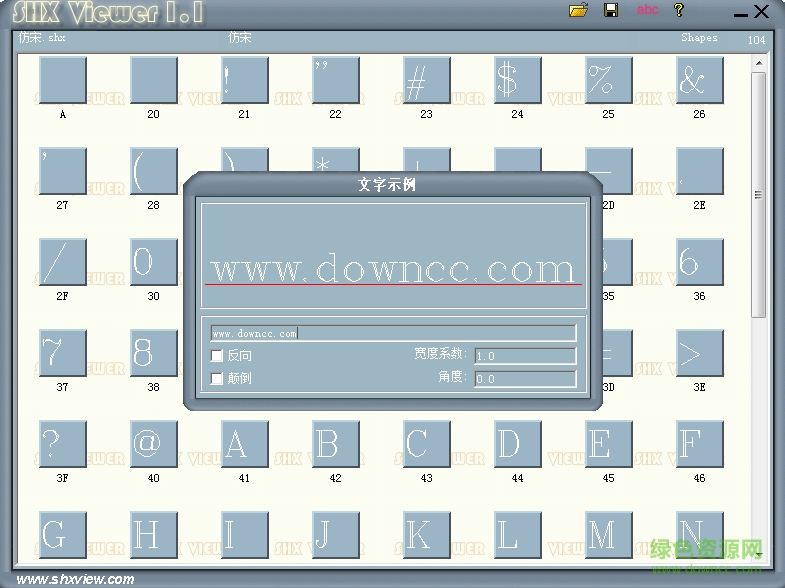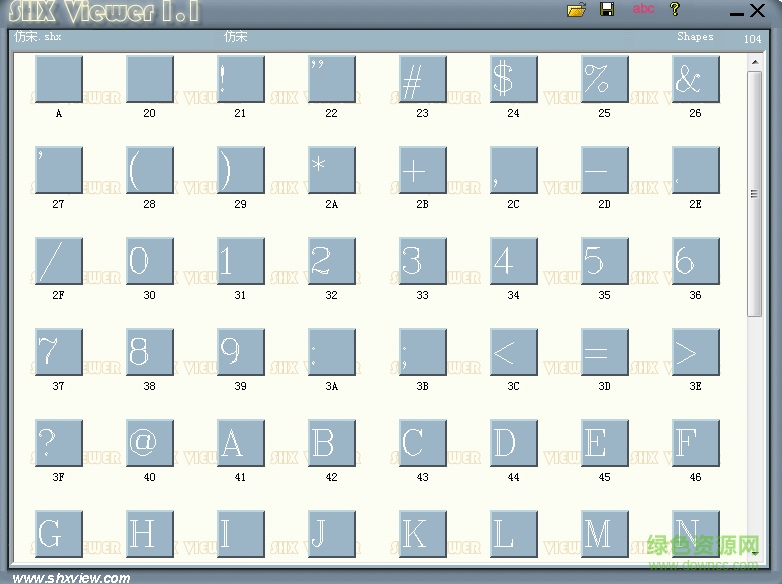
stfangsong是什么字體?stfangsong.shx又叫仿宋.shx字體,該字體結(jié)構(gòu)緊密,字形清新美觀,應(yīng)用效果良好,需要這款字體的朋友快來綠色資源網(wǎng)下載吧!
仿宋是主要的中文字體之一,但是它的使用頻率并沒有宋體、楷體高,而其實(shí)我們?cè)陔娔X上面看到的仿宋是字體設(shè)計(jì)者根據(jù)古籍作品加工的,刪去了一些細(xì)節(jié),使得字體更加平滑,但是卻失去了一些字體原型的風(fēng)韻。
宋體字形較方正,基本可以同時(shí)滿足橫排和直排的需要;
而仿宋的結(jié)構(gòu)特征決定了它必須有一定的傾斜,一旦被調(diào)正會(huì)十分呆板!